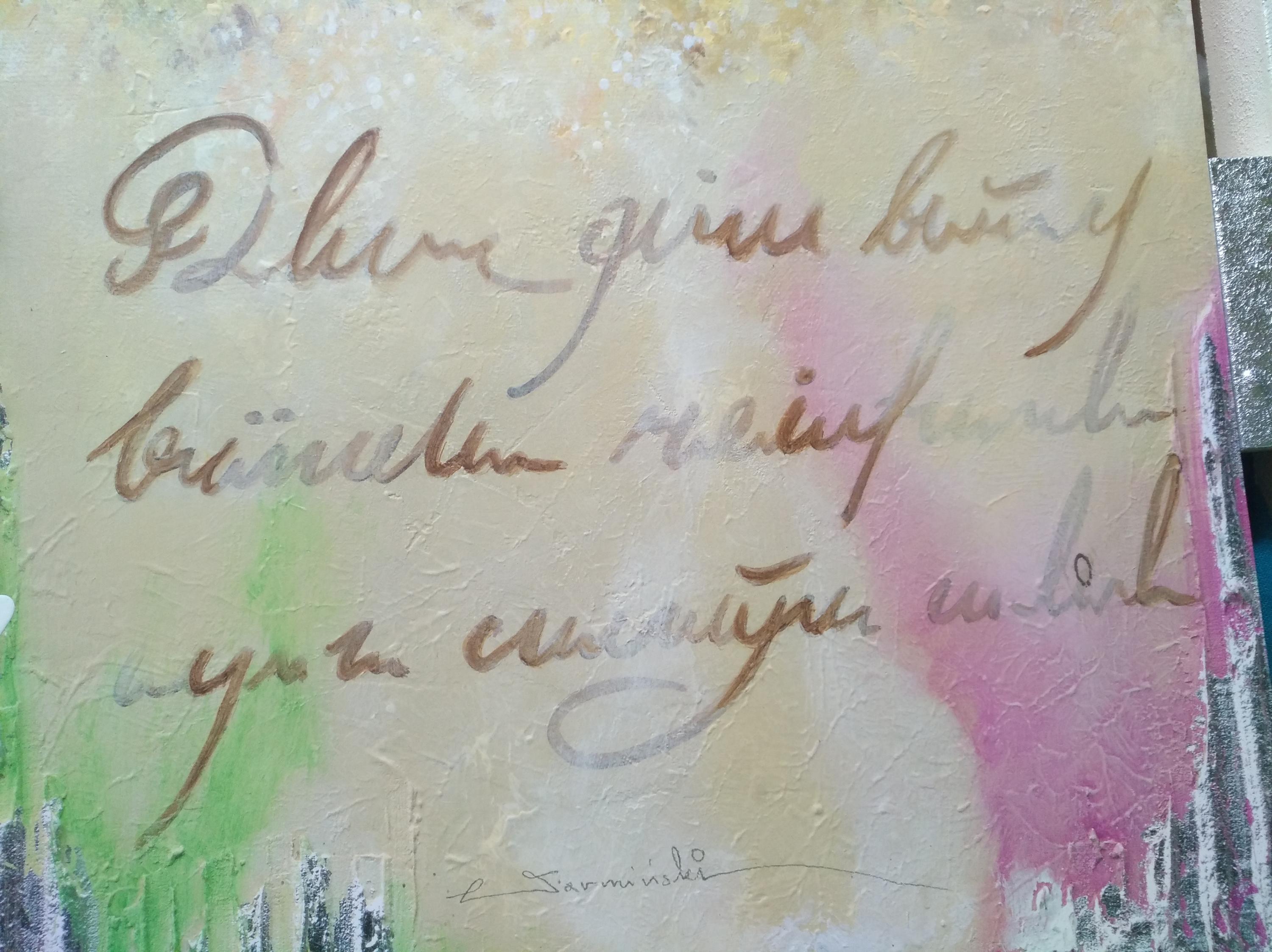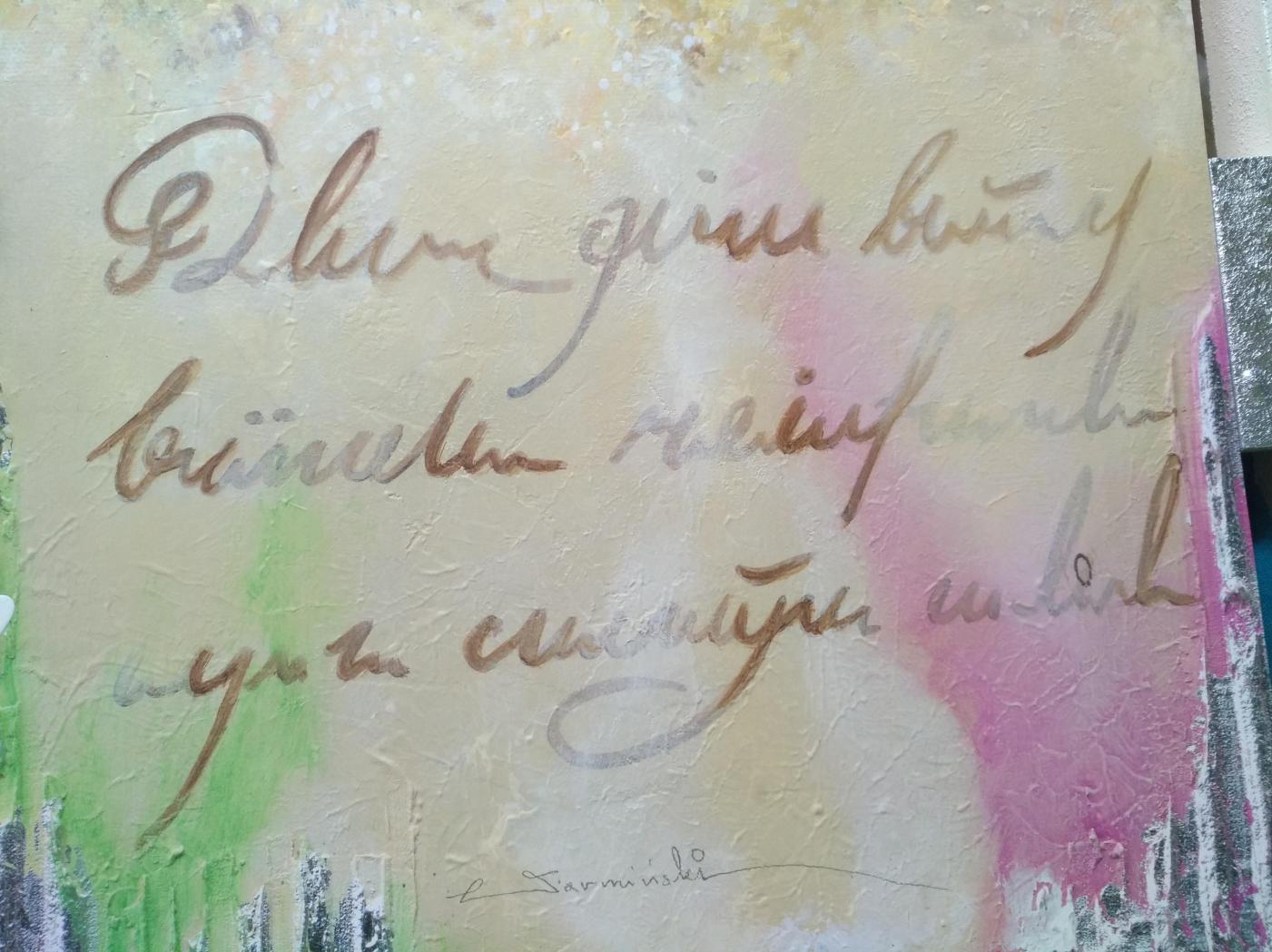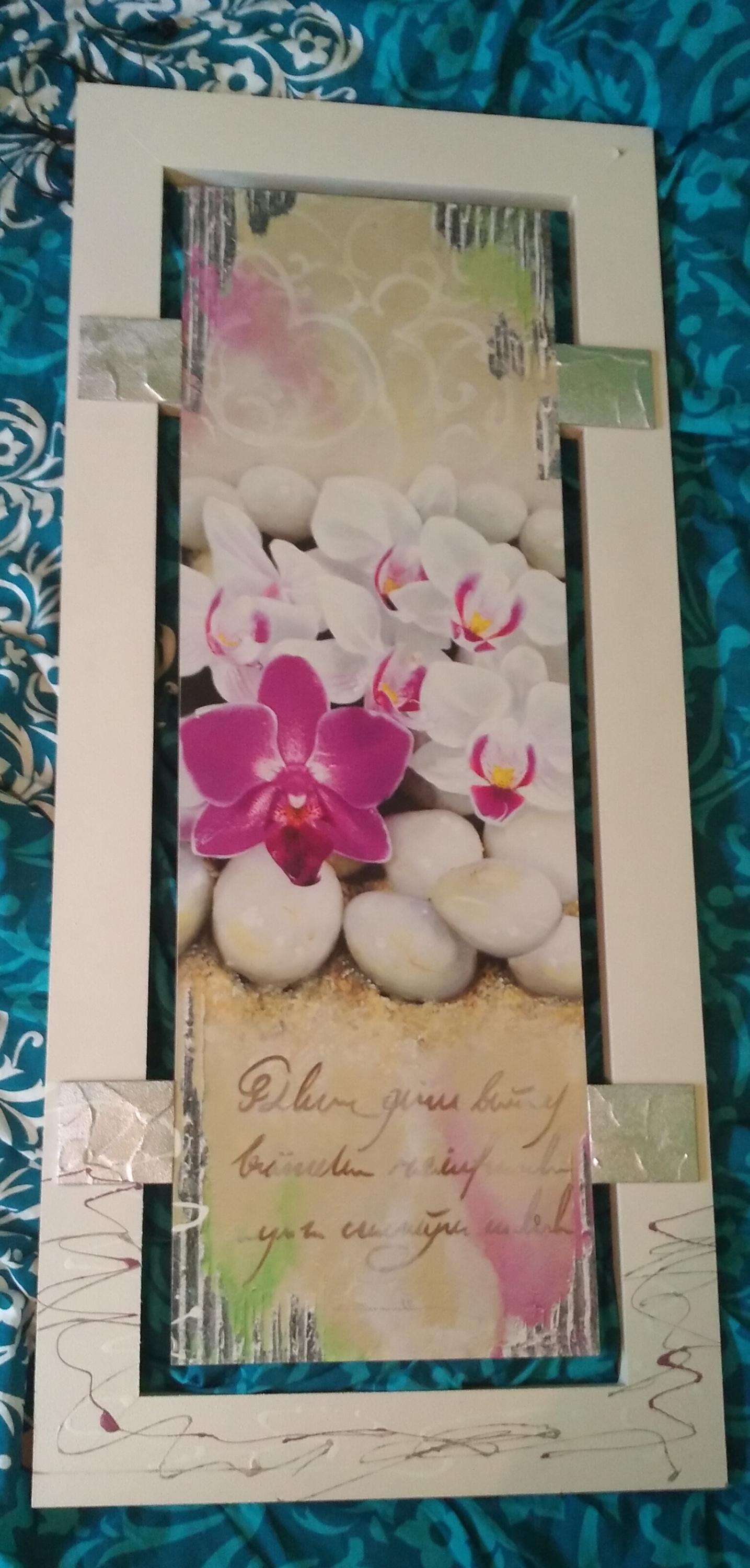
Schrift entziffern
Ich wollte fragen, ob jemand vielleicht diese Schrift entziffern kann. Ich scheitere leider daran.
Was sehen wir da? Ist mit ziemlicher Sicherheit handgeschrieben, also kein Font.
Dieser Schriftzug ist auf einem Bild zu sehen. Kein Altertümchen, eher relativ neu.
Ich habe die Frage in dieses Forum gestellt, da ich diese Schrift nach Stunden des Vergleichens immer noch nicht entziffern konnte. Wenn ich hier falsch bin tut es mir leid °-°
In welcher Sprache ist das verfasst?
Ralf ging wahrscheinlich davon aus, dass du nach der Schriftart fragst und nicht nach dem Inhalt, da du hier im ›Welche Schrift ist das‹-Forum fragst.
Zum Inhalt: Ich habe das Gefühl, dass der Inhalt nebensächlich ist oder da eventuell sogar gar nichts steht, sondern nur so getan wurde, als wäre etwas geschrieben. Vielleicht wurde auch einfach so schnell geschrieben ohne auf Orthografie zu achten und das macht es schwer zu entziffern. Grundsätzlich würde ich davon ausgehen, dass, wenn jemand so schreibt es ihm egal ist ob es gelesen werden kann – und wenn nicht hat er eben Pech gehabt und sollte über seine ›Kunst‹ nachdenken :-?
Zunächst dachte ich, es wäre Latein, aber diese Vermutung hat sich schnell wieder in Luft aufgelöst. Manche buchstaben ähneln dem serbischen Alphabet, allerdings kam ich damit auch nicht viel weiter. Welche Sprache genau benutzt wurde, weiß ich leider nicht.
Gibt’s das komplette Bild zu sehen?
Heißt der Künstler "Warminski"?
Hast du mehr Infos zum Bild?
Danke für Ihren Denkanstoß! Ich habe immer "x Tarminski" gelesen. Durch Ihr Kommentar habe ich Google einmal nach Warminski gefragt und Bingo! Ich habe mir ein paar Werke von ihm angesehen und die Signatur verglichen. Das Bild stammt sicherlich von Arkadiusz Warminski.
Laut eines Kunstforums stammt er aus einer preußischen Adelsfamilie und hat in Danzig gelebt und gearbeitet, bis er sich schließlich in Deutschland nierderließ.
Und ein Bild mit dem kompletten Bild hänge ich hier unten an.
Und ich habe sehr das Gefühl, als ob der Spruch darauf in kyrillisch geschrieben ist, zumindest sind da einige ziemlich klar kyrillische schreibschrift-buchstabebn drin. komplett entziffert bekomme ich das allerdings auch nicht.